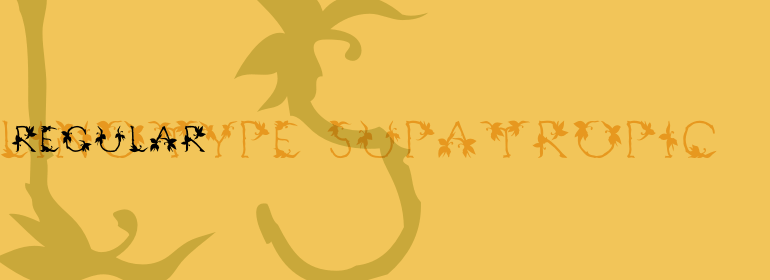
Linotype Supatropic™
Linotype Supatropic™,这款字体结构工整、笔画清晰,兼顾美观与易读性,适用于标题、正文、海报、包装、LOGO 等多种场景。字形优雅稳定,风格百搭耐看,适配日常排版与创意设计,让文字呈现更舒适、更具质感。Linotype Supatropic™一笔一画,皆是细节,以均衡的比例、流畅的线条打造舒适视觉体验,字形端正大气,风格简约现代。无论是商业设计、品牌宣传还是日常排版,都能轻松驾驭,让文字更有格调与力量。Linotype Supatropic™字体下载。
字体品牌: Linotype(Monotype) 设计师:Laxa,Isabell 字体分类:衬线体 字体属性:外文 字符集:Unicode 发布时间: 2018